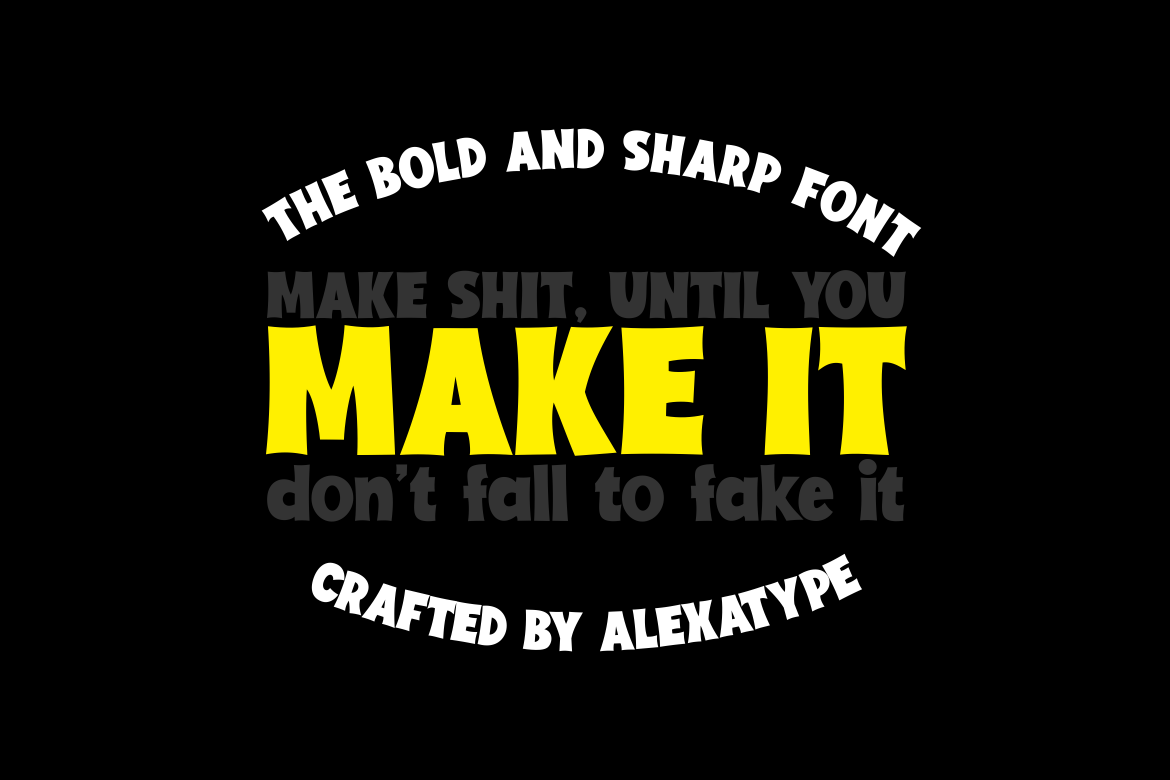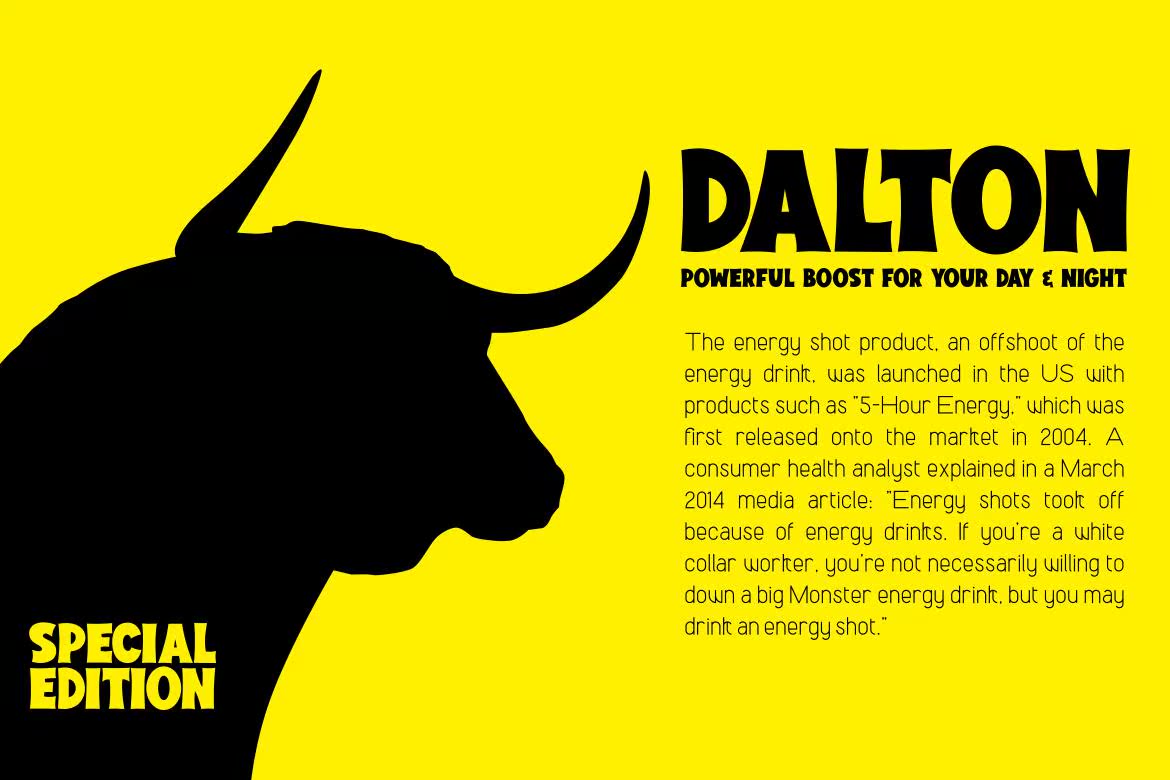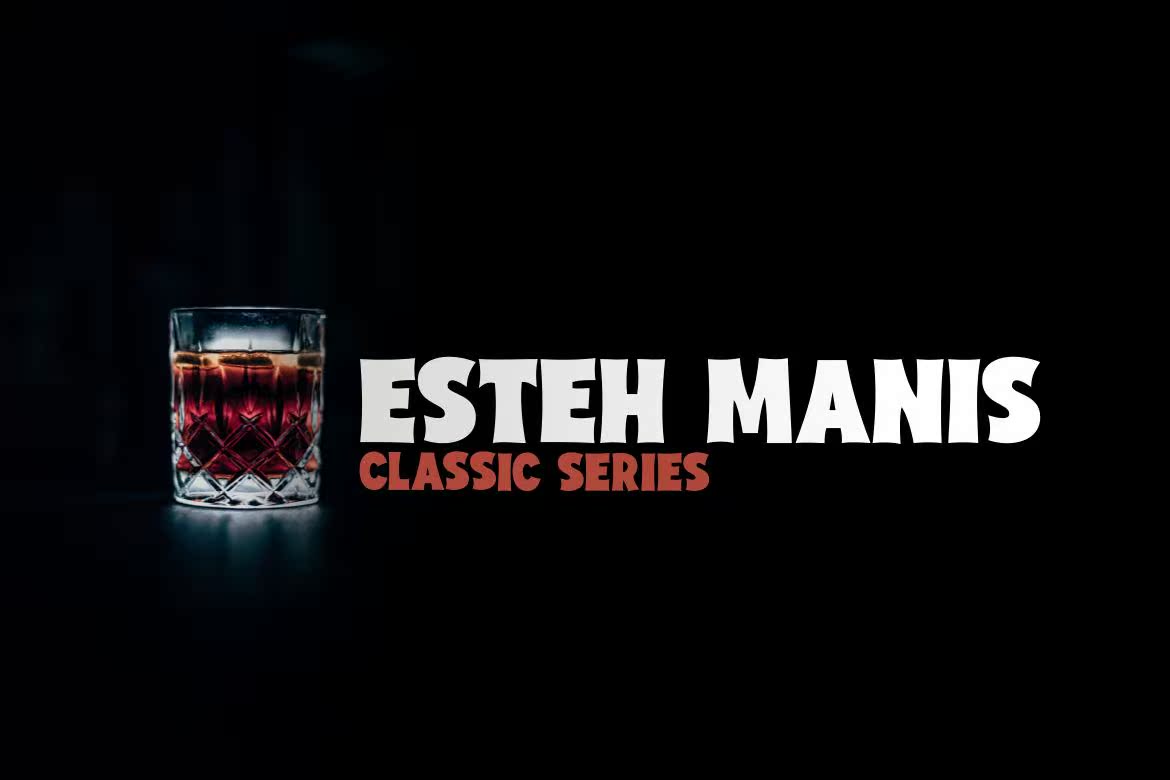
布朗森,我是一个爱开玩笑的人,但却想被别人认真对待。弯曲的身躯和尖尖的角,创造了一些强烈的信息,但这是错误的。这不是维多利亚式的风格,我们永远都会变得严肃起来!它仍然非常适合于海报、游戏拼接、卡通动画、信用标题、杂志等。布朗森是一个有趣的人,但却希望被其他人认真对待。曲线体和尖角角角,创造了一些强烈的信息,但不太可能。它不是维多利亚式的,我们永远都会认真的!它仍然非常适合海报、游戏机、卡通电影、credittitle、杂志等。